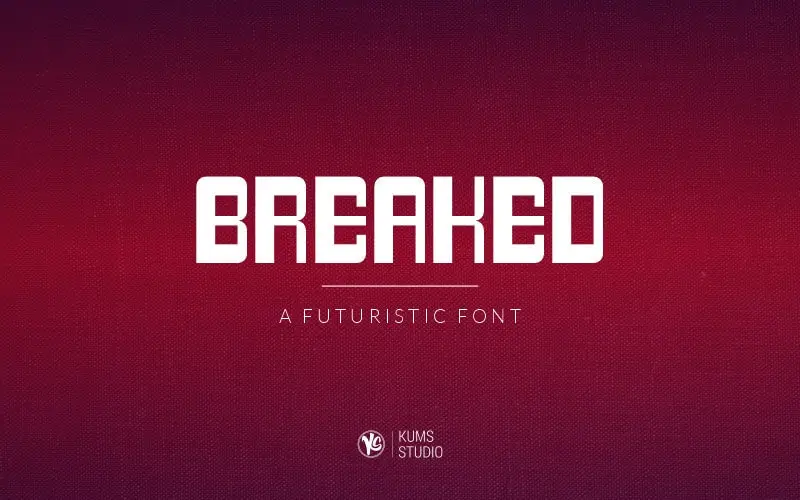
Breaked Display Font – Download Grátis
Bem-vindo à Breaked Display Font, uma elegante escolha para projetos que exigem impacto visual. Perfeita para criações de marca, logotipos, designs de casamento, postagens no Facebook e Instagram, anúncios, embalagens de produtos, design de produto, etiquetas, fotografias e até mesmo marcas em água, esta fonte traz um toque de confiança. Ideal para qualquer projeto que precise de uma impressão forte e imediata. Criada pela kumsstudio, a Breaked Display captura essas características sem perder sua autenticidade e beleza única. Seja você designer gráfico ou profissional de marketing, esta fonte é perfeita para criar mensagens impactantes que chamem atenção nos momentos certos. Descubra agora como a Breaked Display Font pode ajudar a destacar seu trabalho nas plataformas digitais e fora delas.